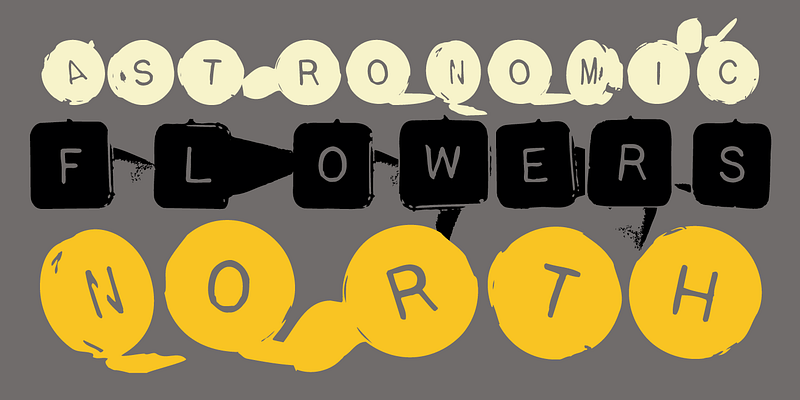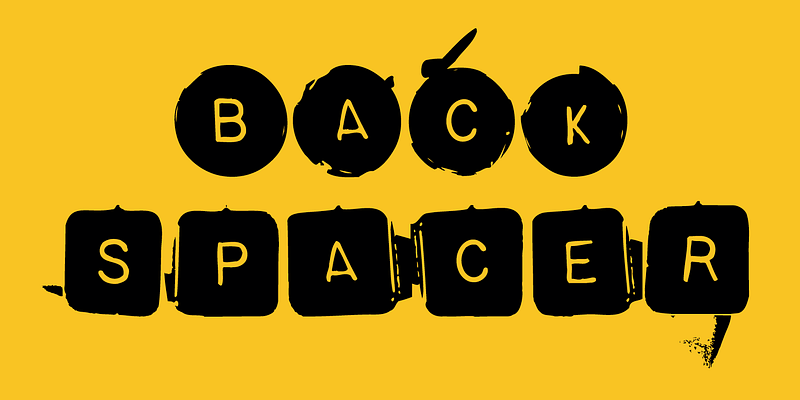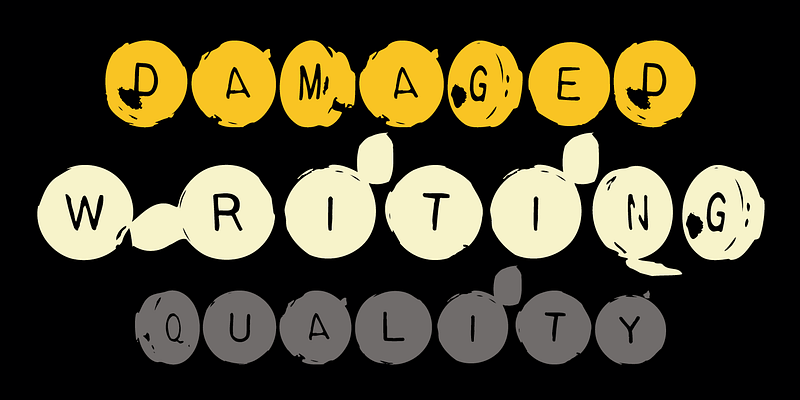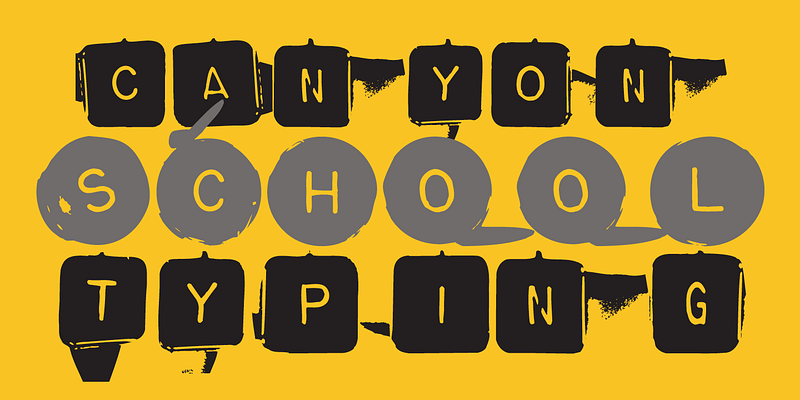
Backspacer는 1993년에 디자인되었습니다. 여러 해 전, 디자이너 Nancy Mazzei와 Brian Kelly는 우연히 브루클린의 버려진 부지에서 낡은 타자기를 발견하여 2년 동안 아파트 주변에 두었습니다. 이사할 때가 되어 이 낡은 타자기를 버리려고 했지만 너무 아름다워 일부라도 보관하기로 결정했고, 어느 날 카메라 렌즈에 잡힐 때까지 타자기 키는 갈색 가방 안에 이었습니다. 타자기 키의 아름답고 기발한 이미지를 가져온 것은 신의 한 수였습니다. 이 이미지가 Backspacer에 대한 영감이었습니다. Zuzana Licko가 스캔하고 투사하여 제대로 된 서체로 탈바꿈했습니다.